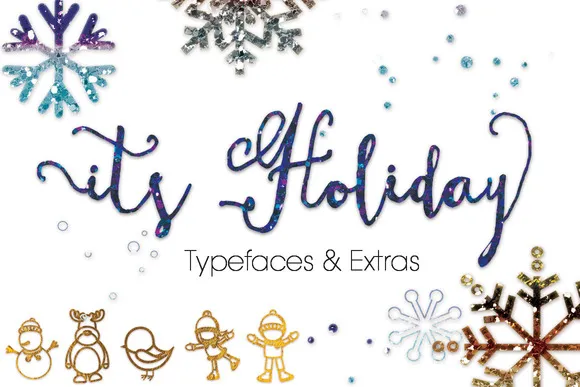
ItsHoliday Font,Fun Calligraphy Font – Download Grátis
A ItsHoliday Font é uma bela fonte de escrita cursiva divertida e criativa, inspirada na arte do calligrafia. Ela traz um toque único com seu estilo de escrita livre de forma natural que combina charme imaginativo e criatividade. Ideal para qualquer projeto que exige um toque artístico, seja em uma frase destacada, título de festa, cartão personalizado ou até mesmo um logotipo elaborado à mão – essa fonte atende a todas essas necessidades. Com sua design de escrita livre e versátil, ItsHoliday é perfeita para tornar qualquer projeto ainda mais especial e único. Perfecto para designers que procuram uma solução única para suas criações digitais.